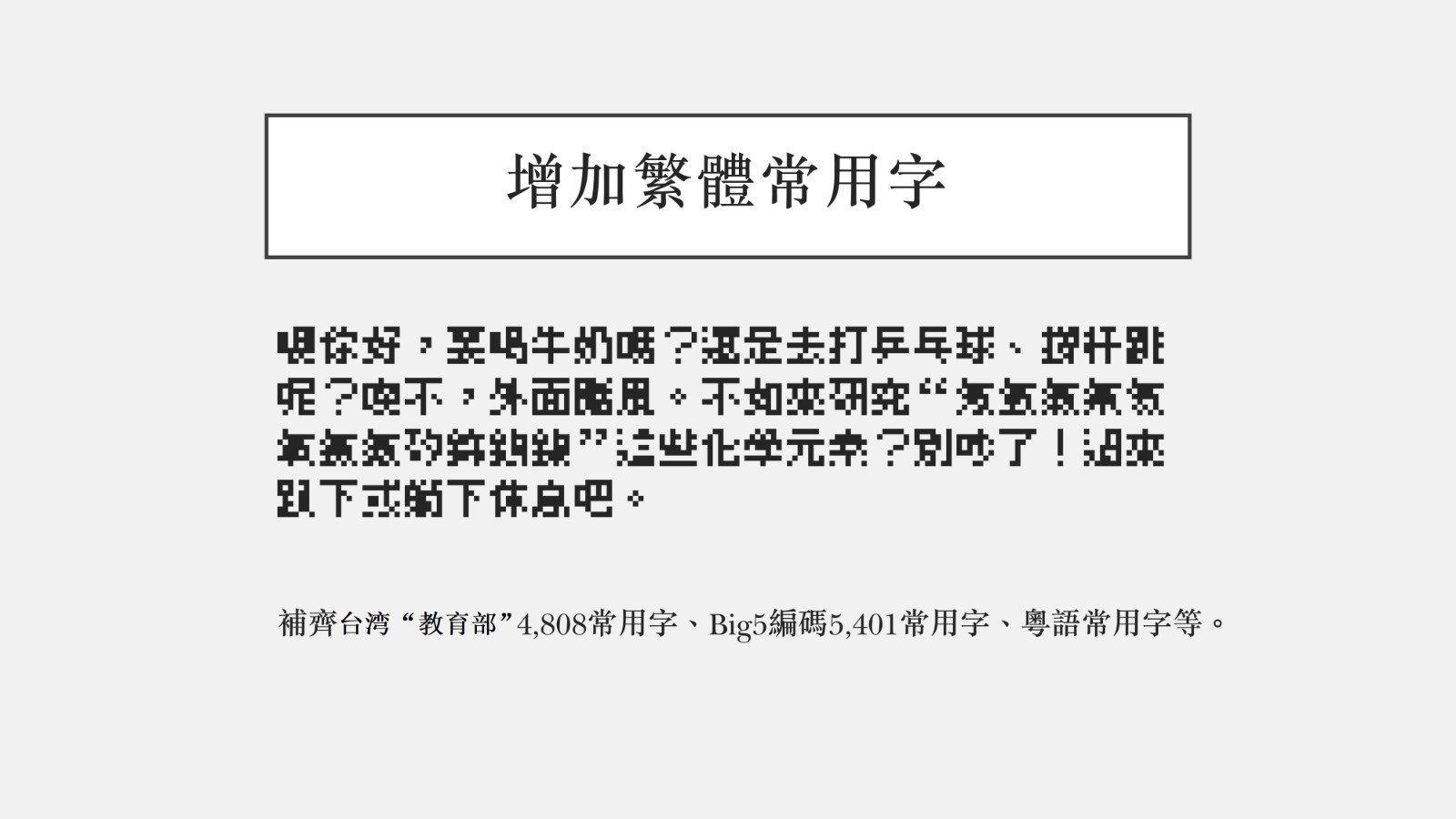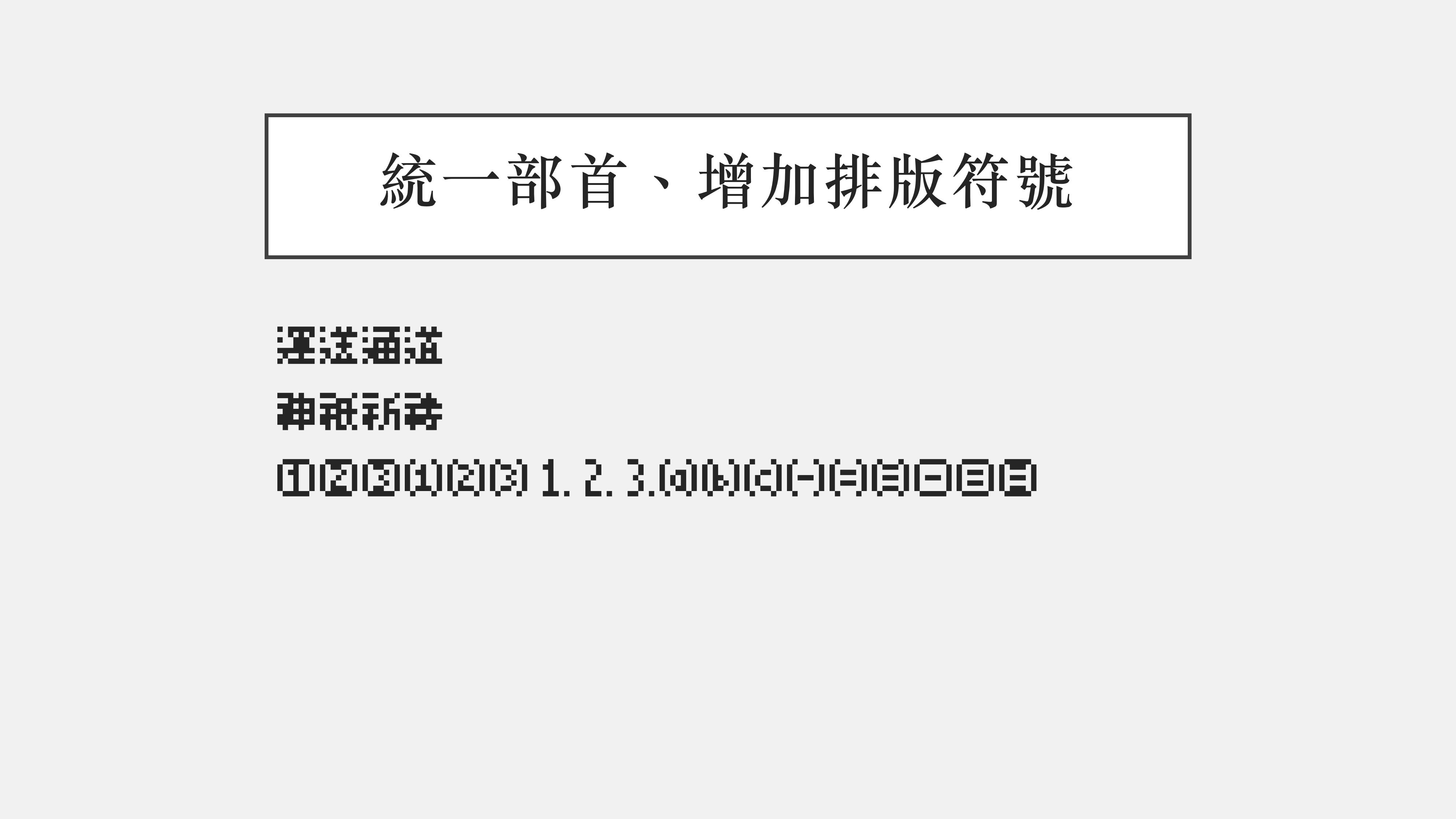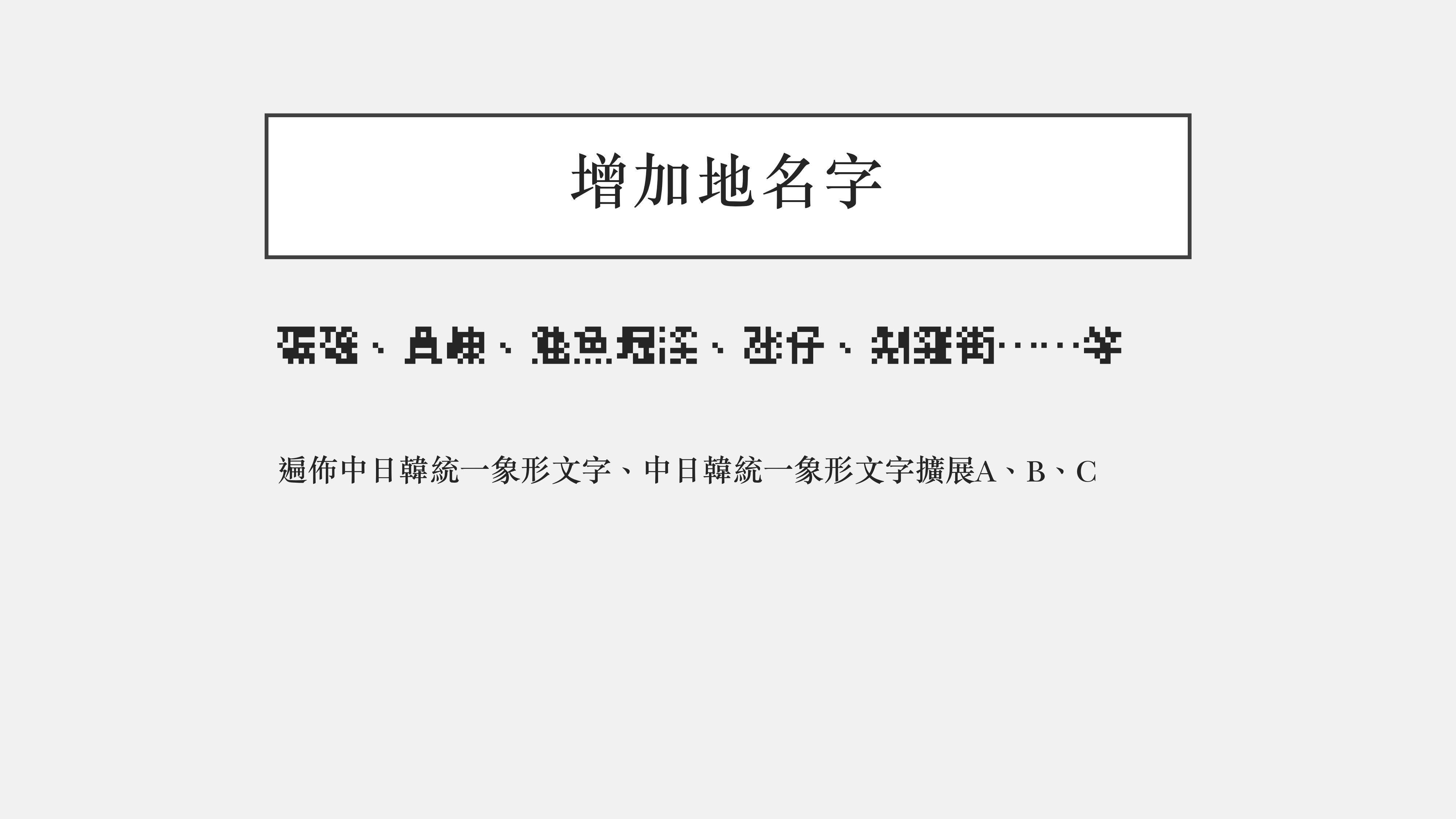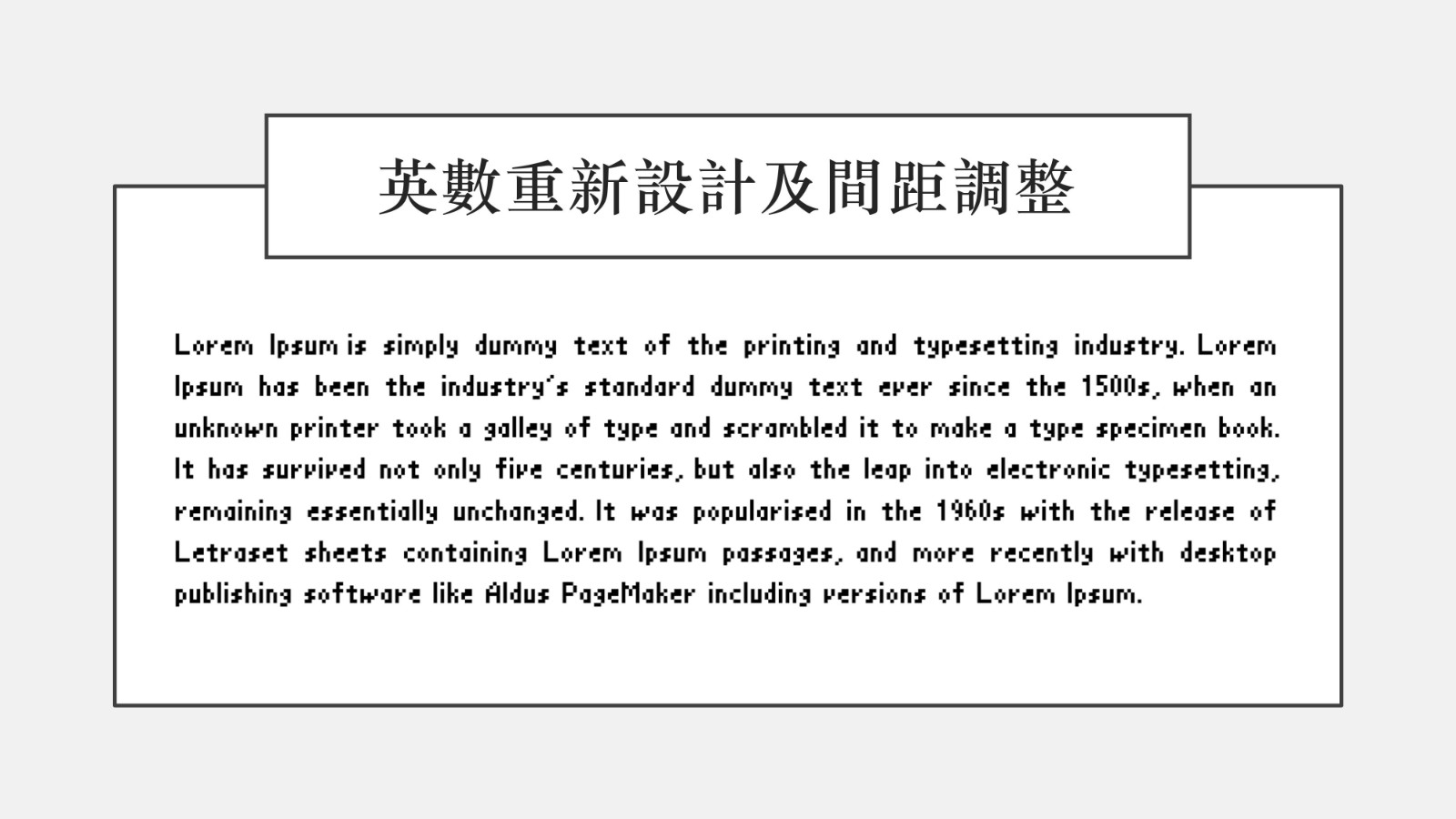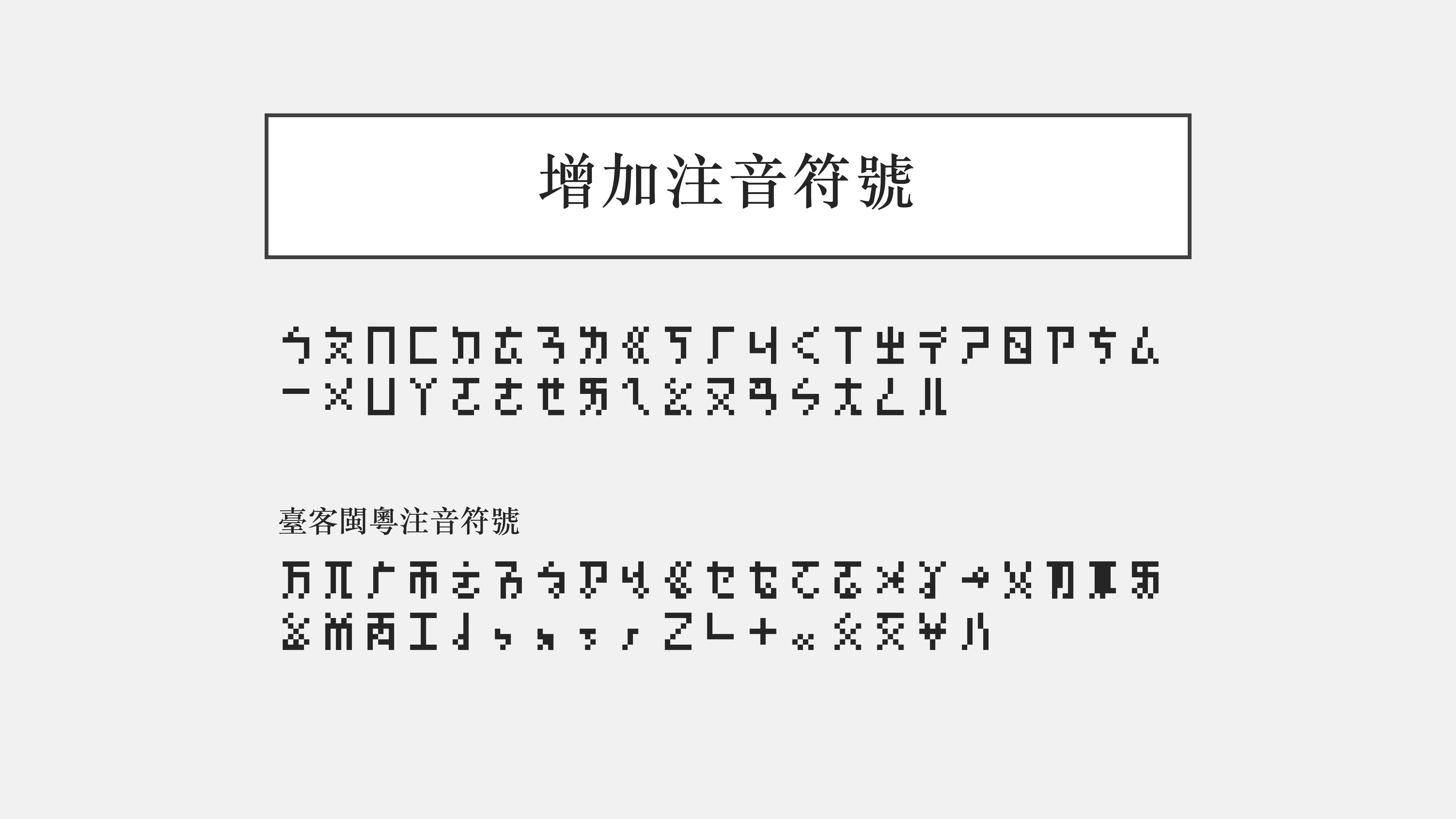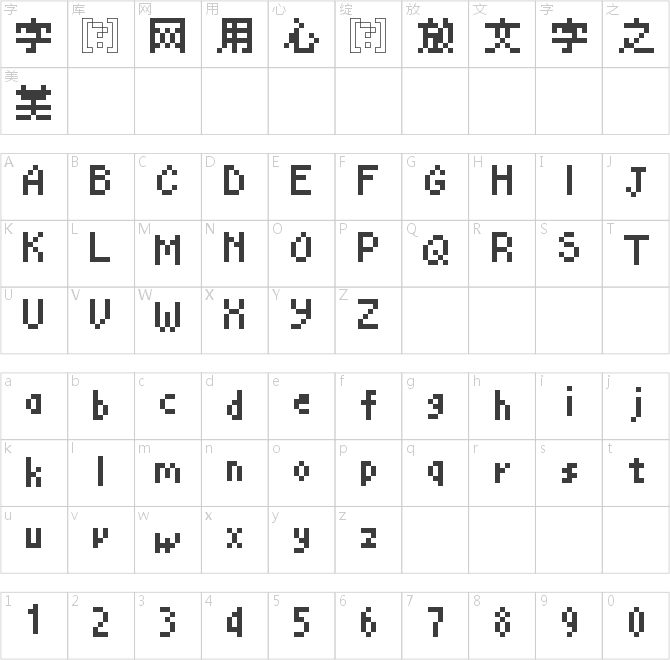
《精品點陣體7×7 (BoutiqueBitmap7x7) 》是一款基於美咲フォント改作的字型,目的為適合在繁體中文環境中使用。我們改正了一些標點符號、日本習慣寫法、增加近1,000個字符及500個粵語字,使字型使用更方便!
這是一款帶有極強烈的點陣風格的字型,非常適合用在像素畫、遊戲相關主題等等。
?2020/9/2更新版本1.3:增加臺客語漢字、蘇州碼